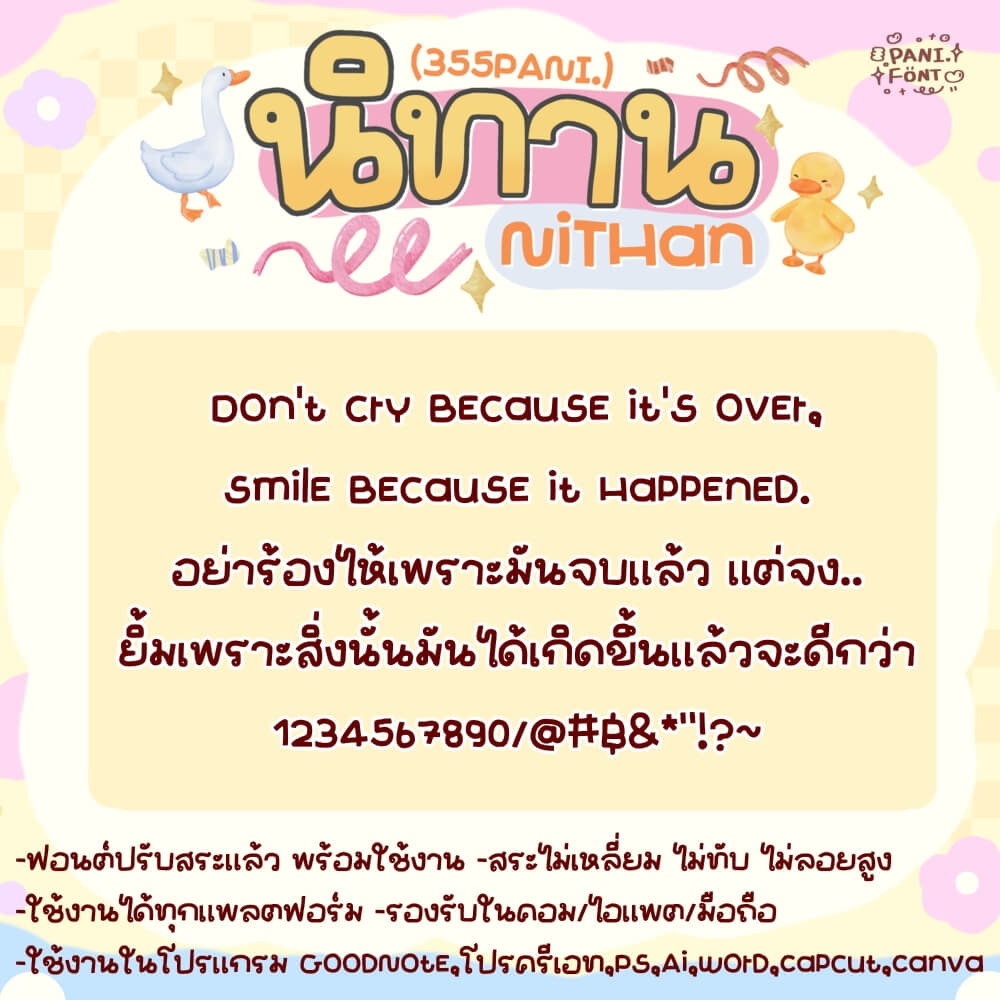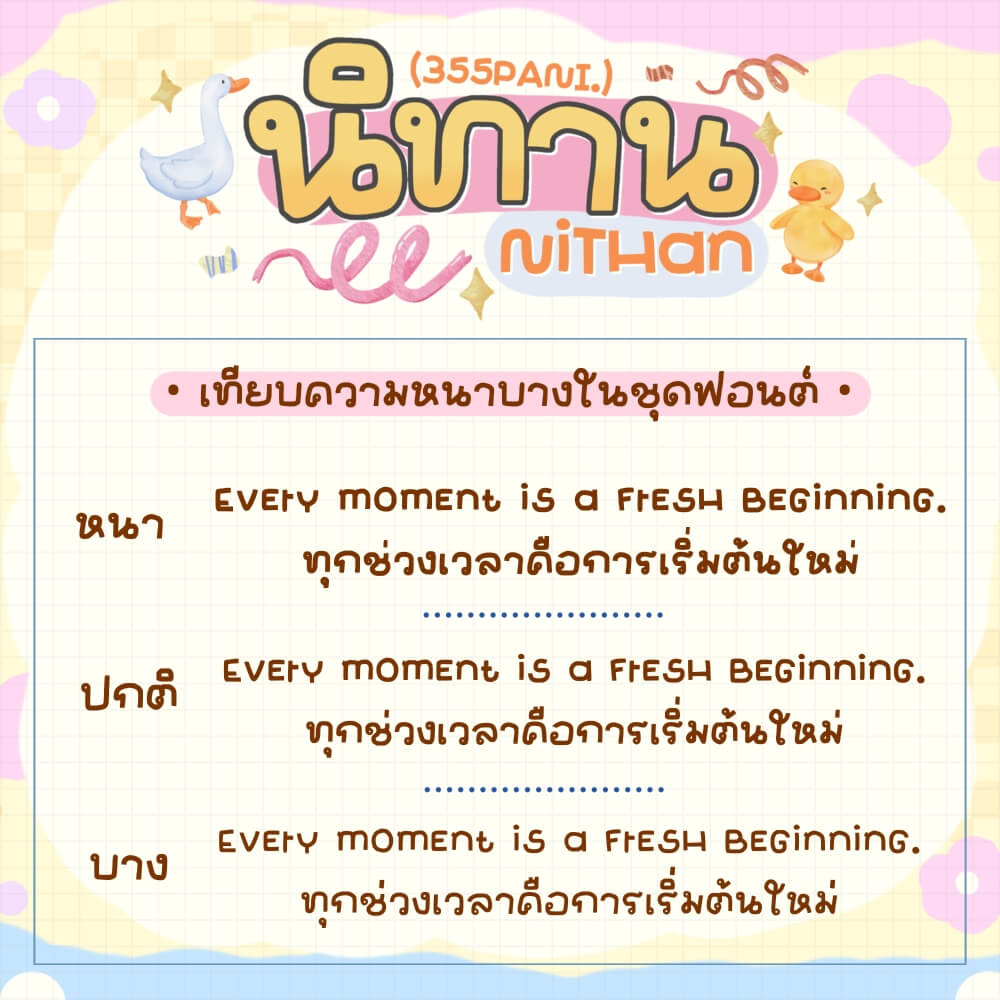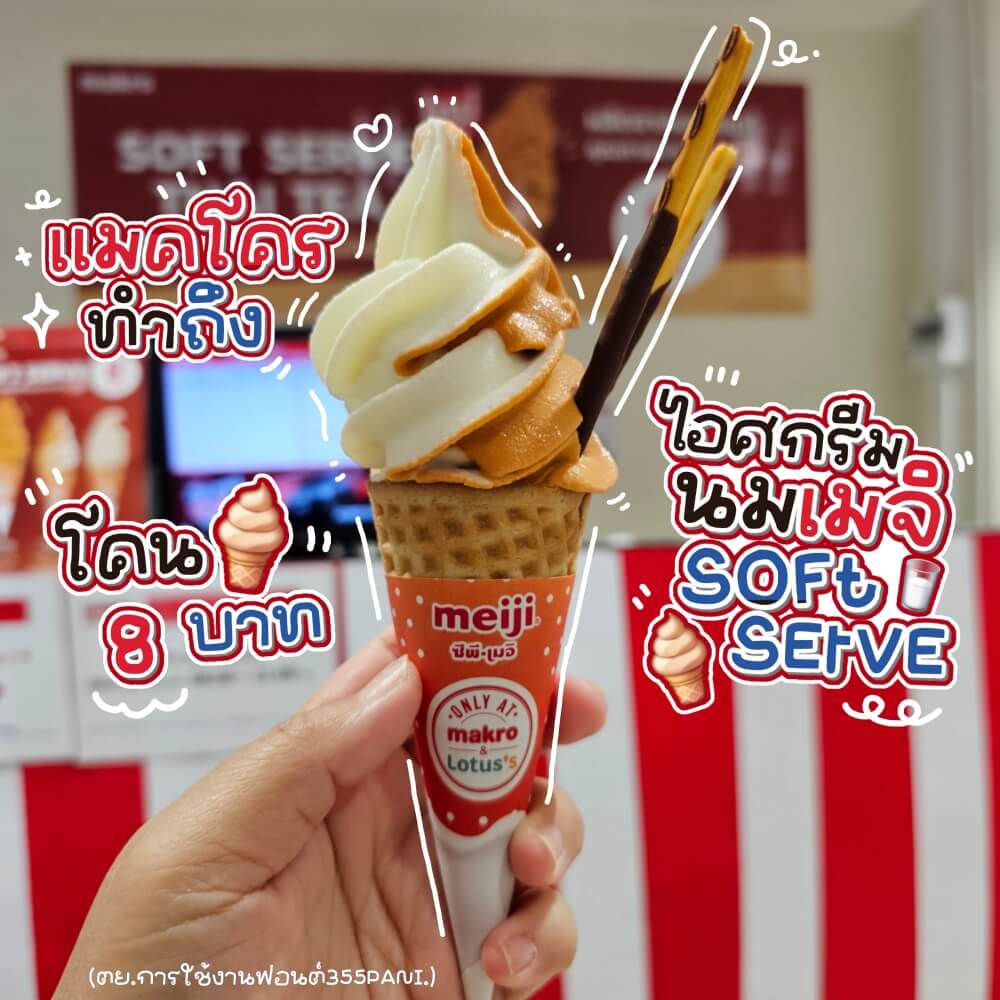
355PANI.นิทาน
ฟอนต์ 355PANI.นิทาน – ฟอนต์เก๋ๆ สวยสมชื่อ หัวกลมเล็กๆ น่ารัก ทำหัวข้อ รึแต่งเปิดคลิปเด่นไม่เหมือนใคร
**เหมาะกับมือใหม่ อยากลองหัดแต่งเองค่ะ แนะนำ
สายใช้เป็นข้อความรายละเอียด ตั้งเป็นฟอนต์เครื่อง จะเก๋ๆ หน่อย แก้เบื่อได้ดี